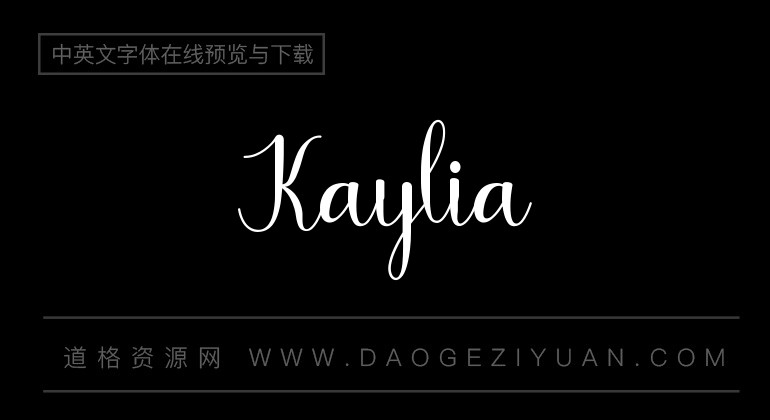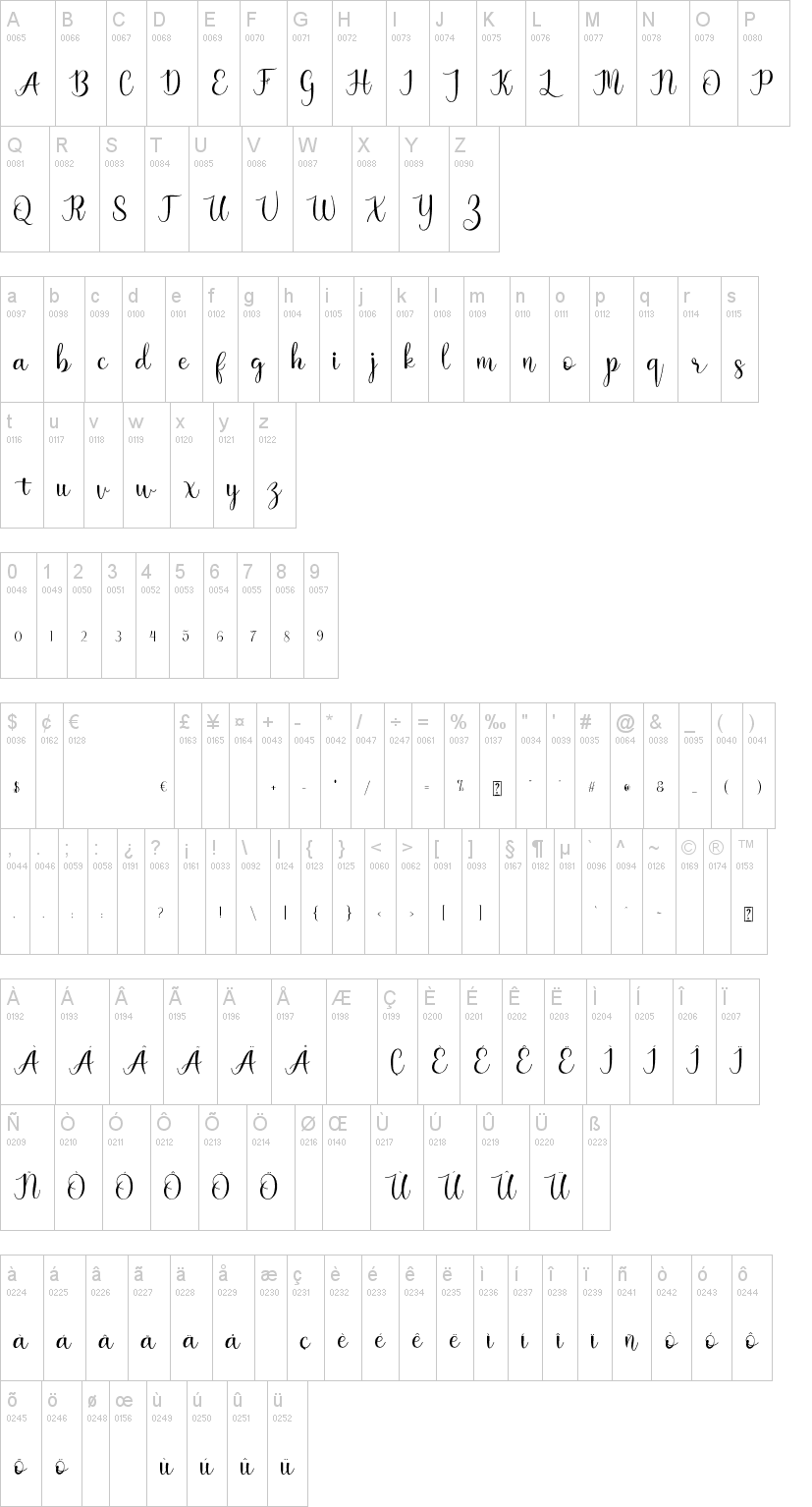
Kaylia字体是一款英文字体,由荷兰设计师Marijke Buurlage设计,它是一款现代字体,具有清晰的线条,优雅的字形,以及极具特色的符号。它的字形极具特色,在英文文本中使用它可以制造出精致的效果。Kaylia字体可以用于商业,艺术,报纸,书籍,网站等各种用途,可以满足不同的需求。内容介绍
Kaylia是一款非常不错的手写艺术字体,具有很好的视觉感,适合于文化类的宣传设计、商业类品牌的广告和产品包装设计以及个性化文字排版等较多场景。